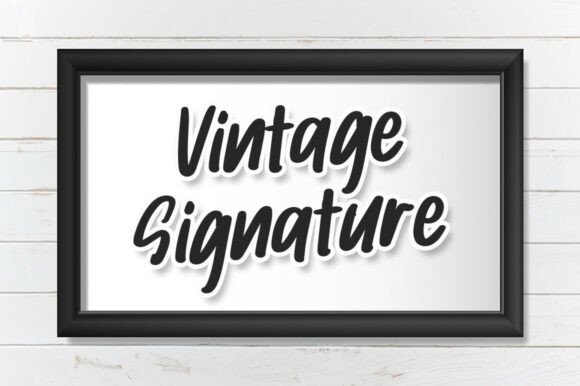
Vintage Signature
適切なデザイン要素を見つけるのは難しい場合がありますが、Vintage Signatureは作品を即座に引き立てる優れたコレクションを提供します。
POD(オンデマンド印刷)製品、結婚式の招待状、またはソーシャルメディアのグラフィックを作成している場合でも、Vintage Signatureは理想的です。